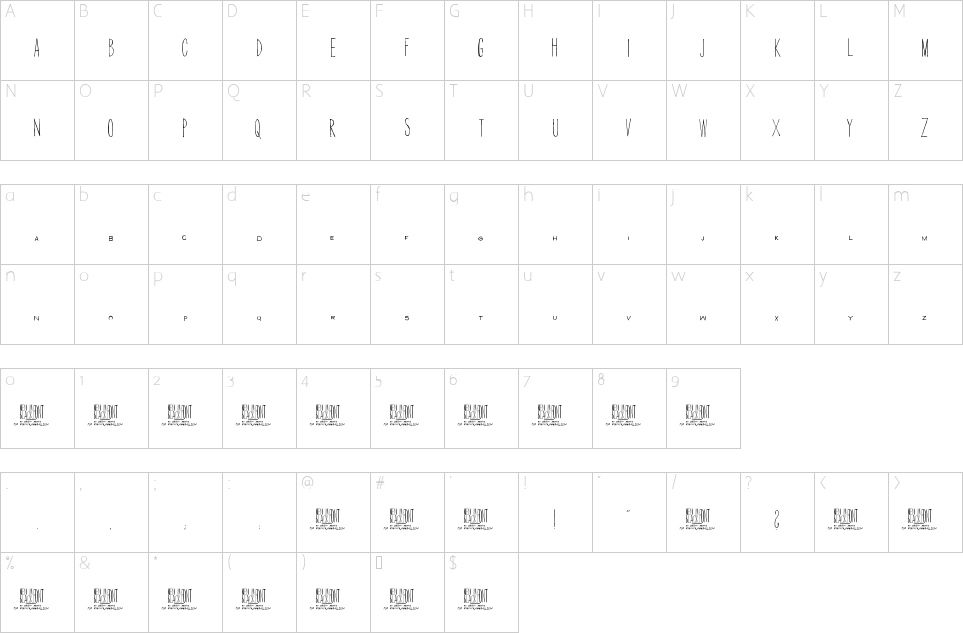
Descubra o Men In Black, uma fonte elegante e moderna que combina um estilo distinto com um toque de sofisticação. Desenvolvida por Jens R. Ziehn da Film Himmel, essa fonte é perfeita para qualquer projeto que valorize um visual clean e contemporâneo. Com seu design minimalista, o Men In Black é ideal para contratos, relatórios ou qualquer outro texto formal que deseja dar um toque atraente e moderno. Para usuários Windows e Mac, é um grande prazer oferecer esta fonte de graça. Desenvolvida por um designer não informado, mas de uma qualidade excepcional, esta font foi projetada para oferecer um visual agradável e funcional. Com mais de 73,204 downloads, é evidente que designers e criativos encontraram nesta font uma opção confiável para suas necessidades de design. O Men In Black é uma excelente escolha para quem busca uma fonte moderna e versátil sem ter que desembolsar qualquer tipo de pagamento.